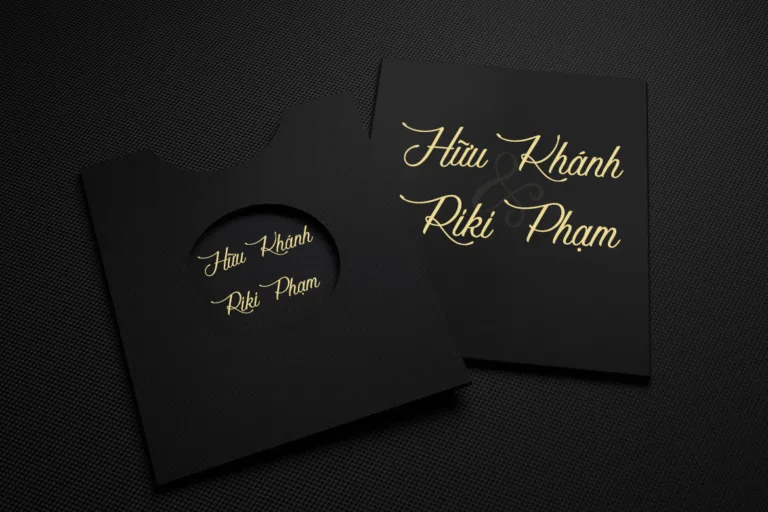
DVN – Sinetimes Mantricia Việt hóa – Font chữ ký bay bổng và lãng mạng
Sinetimes Mantricia là một font chữ calligraphy sang trọng với những đường nét mềm mại, uyển chuyển. Lấy cảm hứng từ nghệ thuật viết tay truyền thống, font chữ này mang phong cách thanh lịch, tinh tế nhưng vẫn hiện đại. Các ký tự được thiết kế với những đường cong mượt mà, kết hợp với các nét nhấn mạnh đầy nghệ thuật, tạo cảm giác quý phái và lãng mạn.
Font chữ này rất phù hợp cho các thiết kế mang tính chất cao cấp như thiệp mời, logo thương hiệu thời trang, mỹ phẩm hoặc các dự án sáng tạo liên quan đến thư pháp. Với sự kết hợp hài hòa giữa nét thanh và nét đậm, Sinetimes Mantricia mang đến sự quyến rũ và độc đáo, giúp nâng tầm giá trị thẩm mỹ cho bất kỳ thiết kế nào.
Nếu bạn đang tìm kiếm một font chữ mang hơi hướng cổ điển nhưng vẫn hiện đại, đây chắc chắn là lựa chọn hoàn hảo.